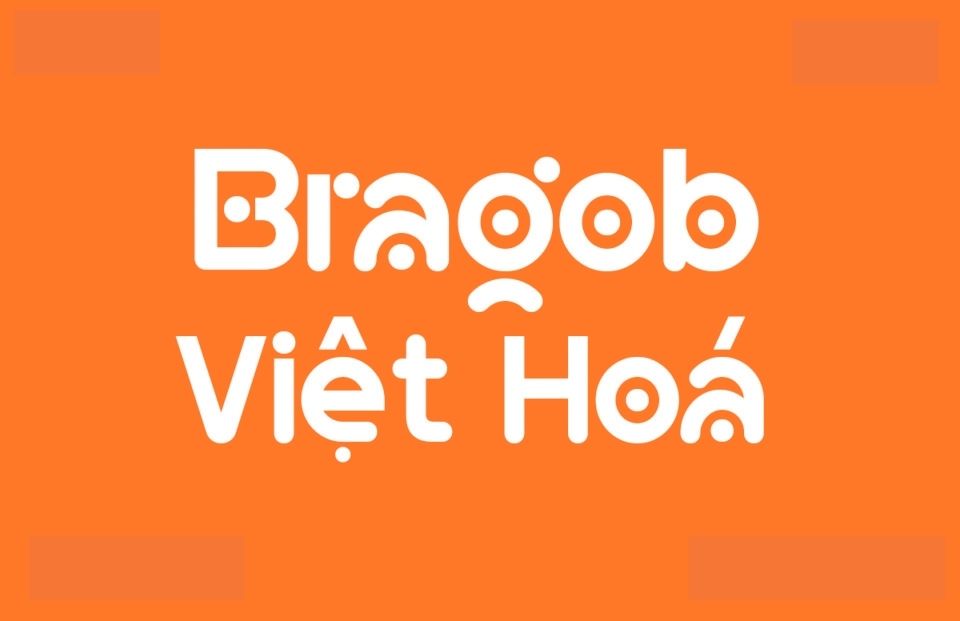
Font Việt hóa 1FTV VIP Bragob là lựa chọn nổi bật dành cho những nhà thiết kế đang tìm kiếm một kiểu chữ cá tính, mạnh mẽ và giàu khả năng nhận diện. Với hệ thống ký tự tiếng Việt được hoàn thiện chỉn chu, font giúp người dùng dễ dàng sáng tạo tiêu đề, poster, bao bì, nội dung truyền thông và nhiều ấn phẩm thị giác chuyên nghiệp mà không phải lo lắng về lỗi dấu.
Sở hữu hình dáng chữ độc đáo cùng tinh thần hiện đại, 1FTV VIP Bragob phù hợp với các thiết kế cần tạo ấn tượng ngay từ ánh nhìn đầu tiên. Đây không chỉ là một bộ font Việt hóa tiện dụng mà còn là công cụ giúp thông điệp trở nên nổi bật, có phong cách và dễ ghi nhớ hơn.
Font Việt hóa 1FTV VIP Bragob – Kiểu chữ cá tính cho thiết kế sáng tạo và nổi bật
Trong thiết kế đồ họa, việc lựa chọn đúng font chữ có thể quyết định đáng kể đến cảm xúc, tính thẩm mỹ và hiệu quả truyền tải thông điệp. Font Việt hóa 1FTV VIP Bragob mang đến diện mạo khác biệt với cấu trúc chữ giàu cá tính, thích hợp sử dụng ở những vị trí cần thu hút sự chú ý như tiêu đề chính, tên thương hiệu, khẩu hiệu, bìa ấn phẩm hoặc nội dung quảng cáo.
Điểm đáng chú ý của bộ font này là khả năng hiển thị tiếng Việt đầy đủ, giúp người dùng trình bày nội dung tự nhiên và thuận tiện hơn. Những dấu thanh, nguyên âm có dấu và ký tự đặc trưng của tiếng Việt được xử lý để hài hòa với phong cách tổng thể, hạn chế tình trạng dấu bị lệch, quá cao, quá thấp hoặc không đồng nhất với thân chữ.
Hỗ trợ tiếng Việt đầy đủ, trình bày nội dung rõ ràng
Chức năng quan trọng nhất của Font Việt hóa 1FTV VIP Bragob là hỗ trợ hệ thống ký tự tiếng Việt. Người dùng có thể nhập các nội dung có dấu như tên sản phẩm, thông điệp quảng cáo, câu trích dẫn, tiêu đề sự kiện hoặc tên riêng mà vẫn giữ được vẻ đẹp đặc trưng của kiểu chữ. Điều này đặc biệt hữu ích đối với designer, người làm nội dung, chủ cửa hàng và các đơn vị truyền thông thường xuyên thiết kế ấn phẩm dành cho thị trường Việt Nam.
Quá trình Việt hóa giúp bộ font trở nên phù hợp hơn với nhu cầu sử dụng thực tế. Thay vì phải thay thế ký tự, chỉnh dấu thủ công hoặc kết hợp nhiều font khác nhau trong cùng một thiết kế, người dùng có thể duy trì sự đồng bộ về hình thức. Nhờ đó, bố cục trông chuyên nghiệp hơn, đồng thời tiết kiệm đáng kể thời gian trong quá trình xử lý nội dung.
Phong cách chữ ấn tượng, tăng khả năng nhận diện
1FTV VIP Bragob hướng đến những thiết kế cần dấu ấn thị giác rõ rệt. Đường nét có cá tính giúp nội dung tiêu đề nổi bật hơn so với các kiểu chữ phổ thông, từ đó hỗ trợ xây dựng hình ảnh riêng cho sản phẩm, chiến dịch hoặc thương hiệu. Khi được kết hợp với màu sắc, khoảng cách chữ và bố cục phù hợp, font có thể tạo nên cảm giác mạnh mẽ, sáng tạo, trẻ trung hoặc phá cách tùy theo chủ đề.
Đây là ưu điểm đáng cân nhắc khi thiết kế các nội dung xuất hiện trong môi trường có mức độ cạnh tranh cao, chẳng hạn như bài đăng mạng xã hội, ảnh quảng cáo, banner bán hàng hoặc hình thu nhỏ cho video. Một kiểu chữ khác biệt có thể giúp người xem nhanh chóng chú ý đến thông điệp chính, ghi nhớ tên chương trình và nhận ra phong cách của thương hiệu trong những lần tiếp cận tiếp theo.
Ứng dụng linh hoạt trong nhiều loại ấn phẩm
Font Việt hóa 1FTV VIP Bragob có thể được khai thác trong nhiều dự án thiết kế khác nhau, đặc biệt là các ấn phẩm ưu tiên phần tiêu đề. Tùy vào mục tiêu truyền thông, người dùng có thể điều chỉnh kích thước, màu sắc, độ tương phản và khoảng cách ký tự để tạo ra phong cách phù hợp. Một số ứng dụng tiêu biểu gồm:
- Thiết kế poster, banner, standee và nội dung quảng bá sự kiện.
- Tạo tiêu đề cho bài đăng Facebook, Instagram, TikTok hoặc các nền tảng truyền thông khác.
- Thiết kế bìa sách, bìa truyện, bìa album, thumbnail video và ấn phẩm giải trí.
- Trang trí bao bì, nhãn sản phẩm, menu, bảng giá hoặc vật phẩm trưng bày.
- Sáng tạo logo chữ, slogan, tên chiến dịch và bộ nhận diện mang phong cách cá tính.
Do có đặc điểm tạo hình nổi bật, font phát huy hiệu quả tốt nhất khi được sử dụng có chọn lọc. Bạn nên ưu tiên dùng cho tiêu đề, cụm từ ngắn hoặc điểm nhấn thay vì áp dụng cho toàn bộ đoạn văn dài. Cách sử dụng này vừa giữ được nét độc đáo của font, vừa bảo đảm nội dung dễ đọc và không làm tổng thể thiết kế trở nên nặng nề.
Dễ kết hợp với các font chữ bổ trợ
Một ưu điểm khác của Font Việt hóa 1FTV VIP Bragob là khả năng đóng vai trò font chủ đạo trong hệ thống phân cấp nội dung. Người thiết kế có thể sử dụng Bragob cho tiêu đề lớn, sau đó kết hợp với một font sans serif hoặc serif đơn giản ở phần mô tả, thông tin chi tiết và nội dung dài. Sự tương phản giữa kiểu chữ cá tính và kiểu chữ trung tính giúp bố cục có nhịp điệu, rõ thứ tự đọc và thuận tiện hơn cho người xem.
Để đạt hiệu quả thẩm mỹ tốt, người dùng có thể áp dụng quy trình cơ bản sau:
- Xác định nội dung quan trọng nhất cần được làm nổi bật trong thiết kế.
- Sử dụng 1FTV VIP Bragob cho tiêu đề hoặc thông điệp ngắn có kích thước lớn.
- Chọn một font phụ dễ đọc cho phần mô tả, địa chỉ, thời gian hoặc thông tin liên hệ.
- Điều chỉnh khoảng cách chữ và khoảng cách dòng để bố cục thông thoáng.
- Kiểm tra khả năng hiển thị trên cả màn hình lớn, điện thoại và bản in trước khi xuất file.
Việc phối font hợp lý không chỉ làm nổi bật đặc điểm của Bragob mà còn giúp toàn bộ ấn phẩm cân bằng hơn. Người dùng nên giới hạn số lượng font trong cùng một thiết kế, đồng thời duy trì sự nhất quán giữa các sản phẩm thuộc cùng chiến dịch hoặc thương hiệu.
Tối ưu quy trình sáng tạo cho designer và người làm nội dung
Nhờ được Việt hóa, bộ font giúp